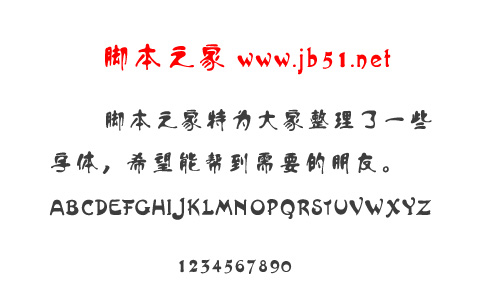
方正流行体简体字体是方正字体库中的一种字体,方正流行体以带有流动感的笔触设计而成。其笔画带有手写的意味,横向笔画左细右粗,竖向笔画上粗下细,笔画间相互融合,流畅舒展富有动感。方正流行体的个性奔放有活力,适用于生活类品牌的广告和产品包装设计。此字体应用广泛,是众多用户的喜爱,喜欢的朋友们可以前来下载使用。